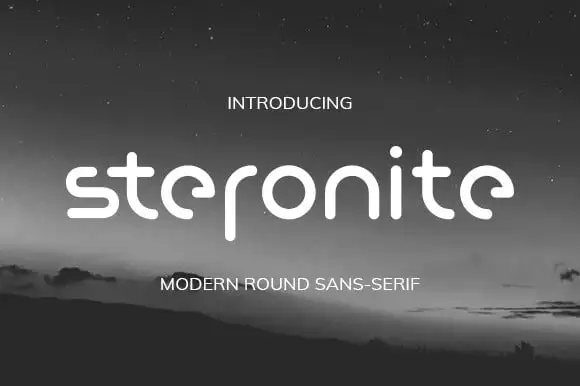
Steronite Sans Serif Font – Download Grátis
A Steronite Sans Serif é uma família moderna de tipo sans serif que junta elementos de estilos antigos e modernos na mesma tipografia. Esta família de letras combina ideias conceituais com simplicidade, oferecendo um formato livre e fluido. A Steronite apresenta linhas afiladas e limpas, além dos toques humanísticos que o tornam ainda mais atraente. Com sua estrutura levemente estreita, ela se destaca por ser versátil em diversas aplicações gráficas. Seu design conceitual e simples permite uma fácil adaptação para um amplo espectro de projetos, sejam eles impressos ou digitais, garantindo que sua presença seja notada entre tantas outras. Adicione a Steronite à sua cartela de fontes, e você vai perceber como ela pode transformar suas ideias criativas em algo ainda mais singular. É uma escolha perfeita para quem busca um equilíbrio moderno e elegante que combina com o melhor do passado sem perder a atualidade necessária nos dias atuais.